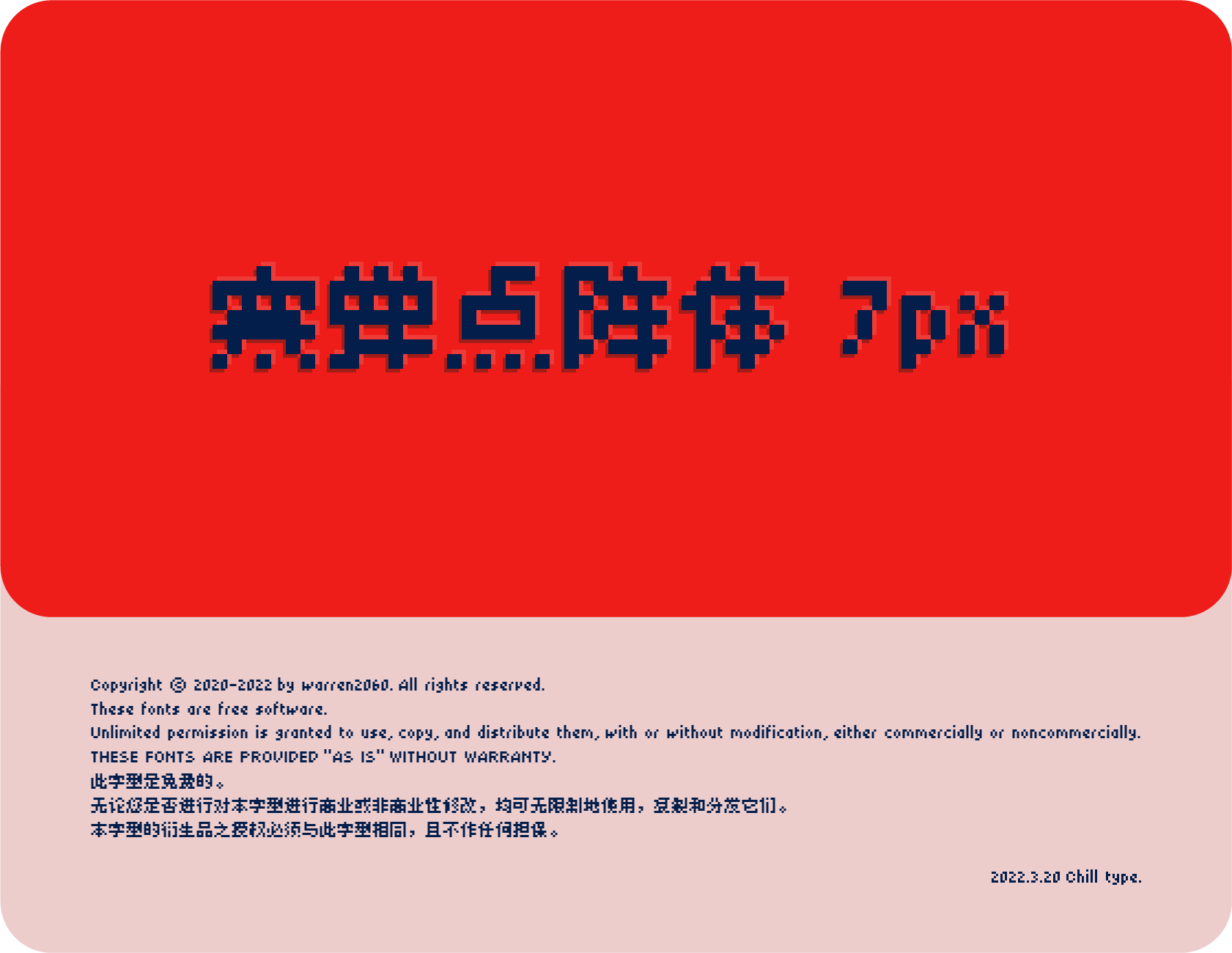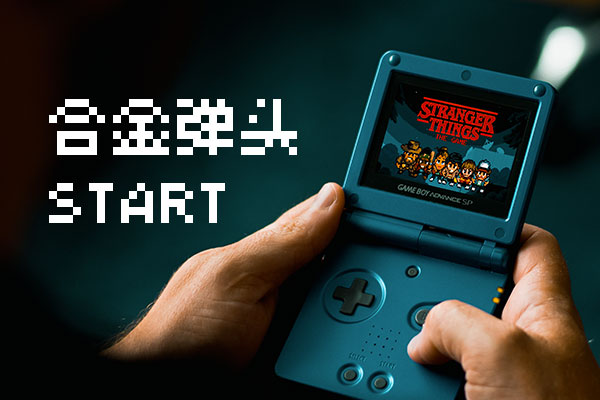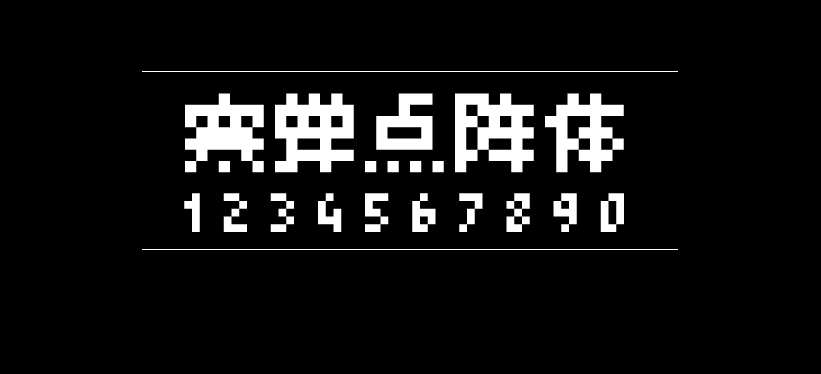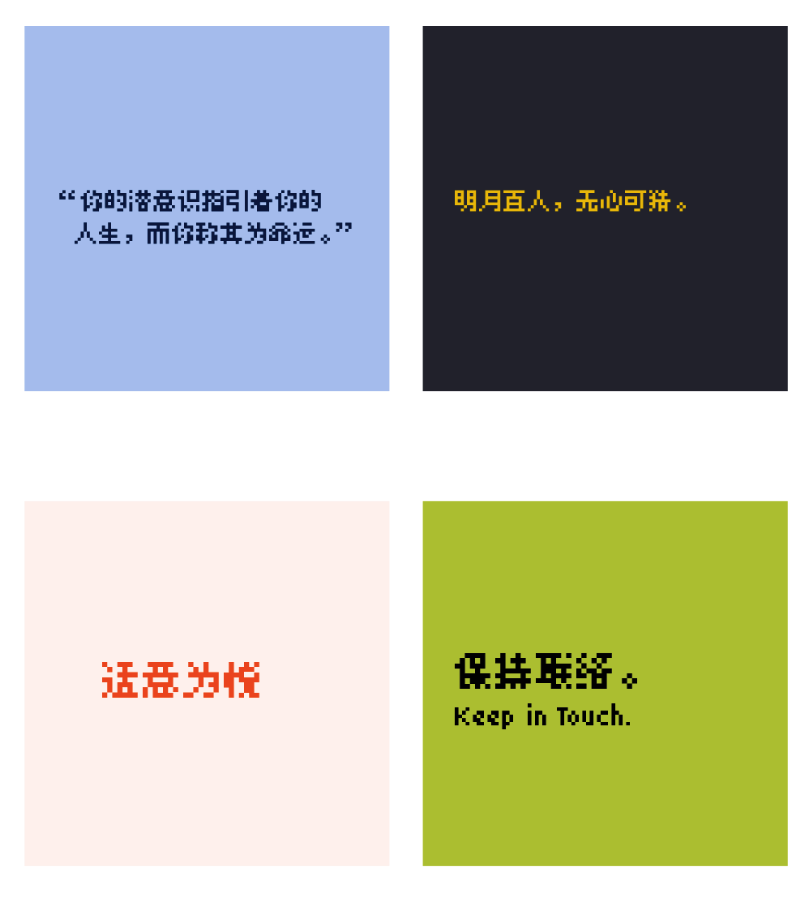
寒蝉点阵体
寒蝉点阵体(Chill Bitmap)的作者是中国大陆的萧熠Siue,该字体是寒蝉字型的又一套像素风格的中文字库。自由字体之前已发布过寒蝉系列的 英文字体chill pixels
寒蝉点阵体基于「美咲フォント」修改的字型,融合部分「精品點陣體7×7」字形和极少一部分「Guanzhi 8px」的字形,重新修改设计了英文部分字形和标点符号使其更加协调统一,筛选GB2312字符集调整了近2000文字使字形更清晰耐看,再设计增加1500多字符
寒蝉点阵体是集日文、繁体、简体、英文共13600个字符的大成之作,使用更方便。感谢以上开源字型的作者!